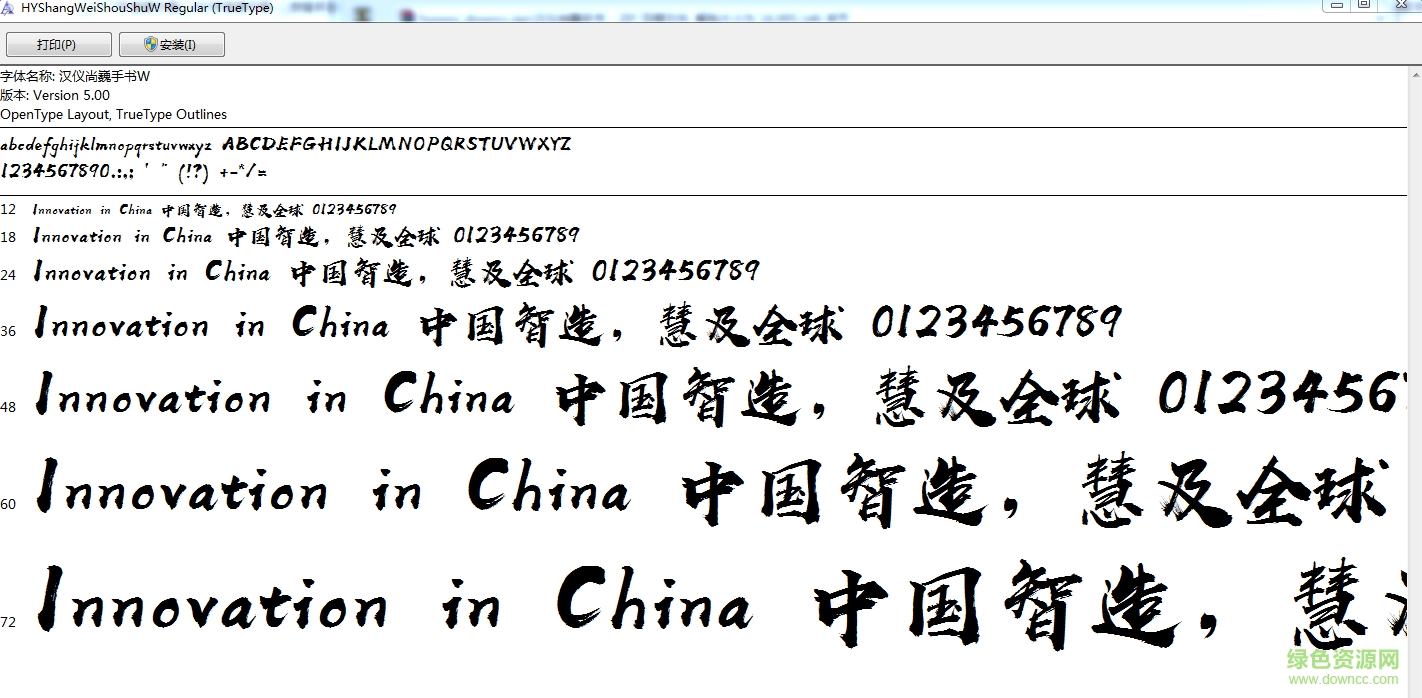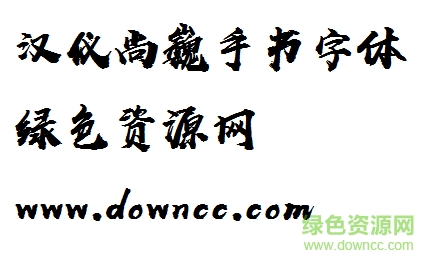
漢儀尚巍手書ttf字體是一款漢儀類藝術風格十足的字體軟件,手書體非常優(yōu)雅大方,適用于海報標題印刷等行業(yè),也深受廣大書法家的喜愛,還有更多好看字體盡情期待,歡迎到綠色資源網下載體驗!
漢儀尚巍手書字體是一款應用于藝術設計方面的簡體中文字體,該字體筆畫粗壯,尾部的甩尾有力且有豐富的筆觸細節(jié),大字效果突出且引人注目;并且最大程度還原作者書寫字形,細節(jié)表現完整,且字庫完整,可以廣泛應用于名片設計、新聞媒體、宣傳海報、ppt、影視制作以及內容用字等領域。